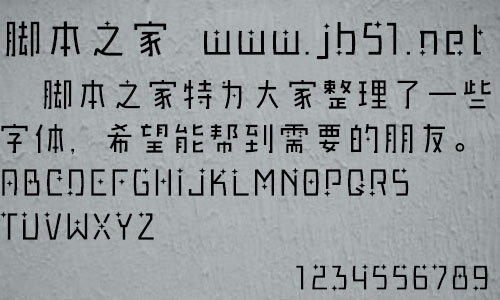
GEETYE歌留多体-闪家族字体,由极字和风字库出品,该字体包括六款字重,具有很好的视觉感,适合应用于艺术设计、平面宣传设计、网页设计,书法字帖等领域,需要的朋友可以前来本站下载。
包括字体
GEETYE歌留多体-闪 准粗
GEETYE歌留多体-闪 纤细
GEETYE歌留多体-闪 常规
GEETYE歌留多体-闪 细体
GEETYE歌留多体-闪 特粗
GEETYE歌留多体-闪 大粗